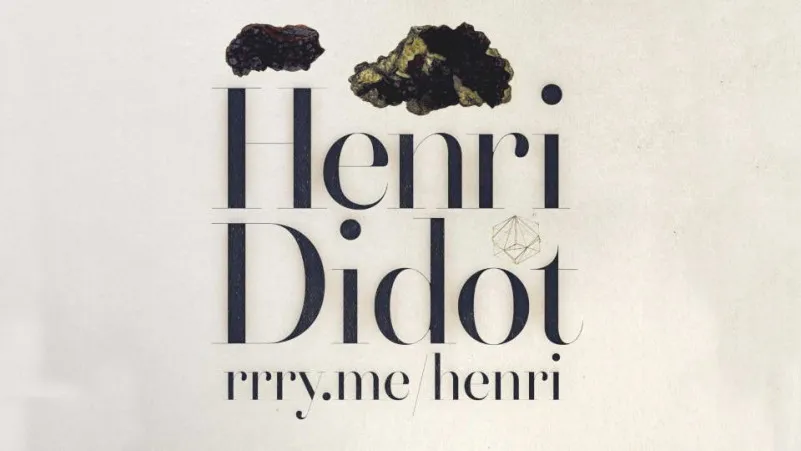
A Henri Didot Font é uma elegante tipografia serifada criada pelo designer Rory Harnden 函Henri Didot foi inspirada no trabalho do criador Alexey Kryukov. Essa fonte vem com um conjunto completo de letras maiúsculas e minúsculas, números e símbolos, alternativas e ligaduras. A Henri Didot é uma escolha perfeita para criar materiais profissionais e elaborados. Como uma serif typeface criada pela 99designs, ela atende a todos os requisitos de um designer ou editor de texto. Se você está procurando por uma fonte para projetos de alto luxo que exija um toque de elegância sofisticada, a Henri Didot é definitivamente o tipo certo.